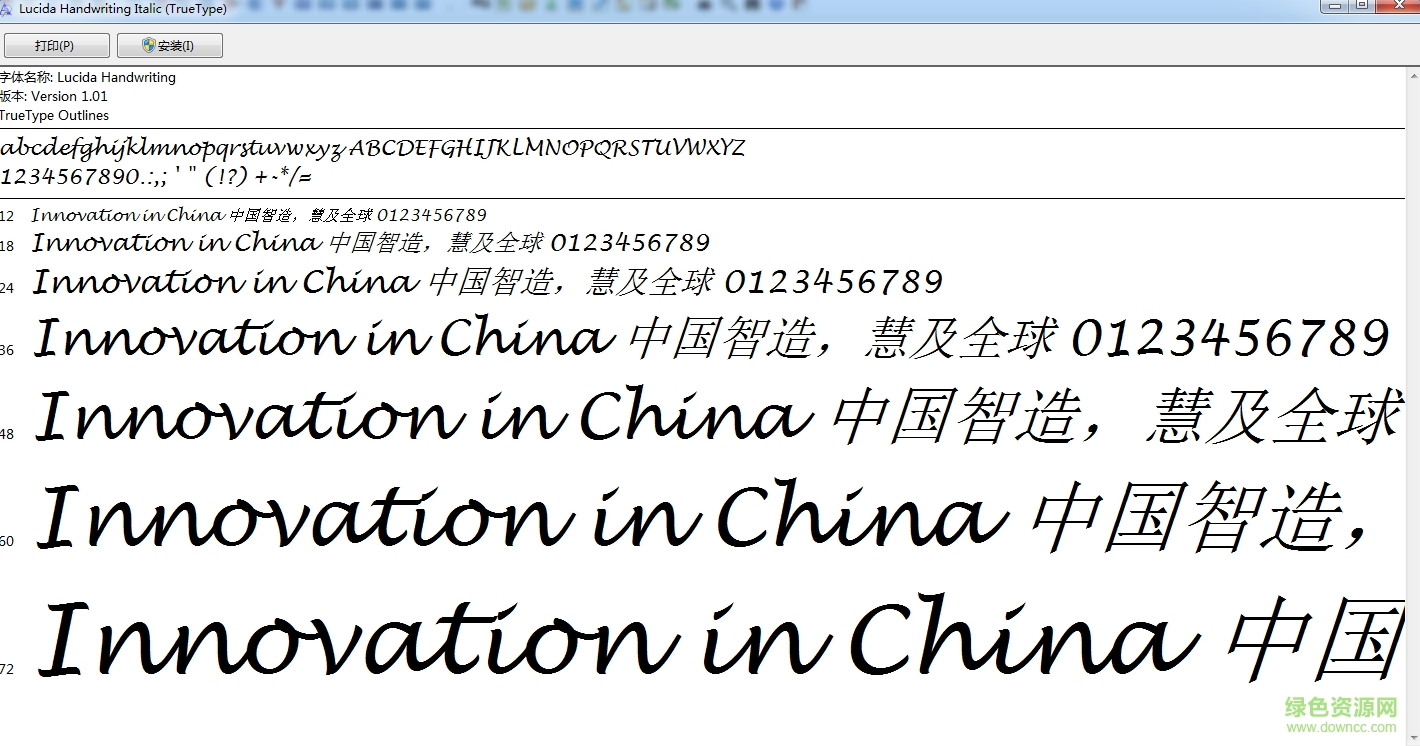
lucidahandwriting italic
lucida handwriting italic字體是整個lucida字體家族中最獨特的字體了,線條連綿,結(jié)構(gòu)簡省,帶有書法風(fēng)格,喜歡這款字體的小伙伴趕緊下載收藏吧!
lucida handwriting字體整個看著比較有曲線,凌亂中不失章法,字形清新優(yōu)美,使用這款字體很能吸引用戶的眼球,引人注目。